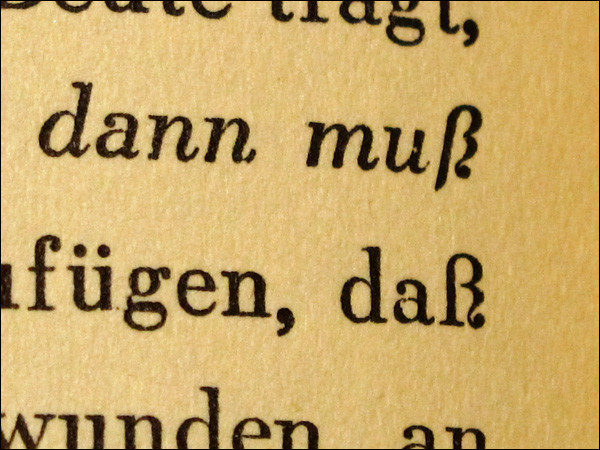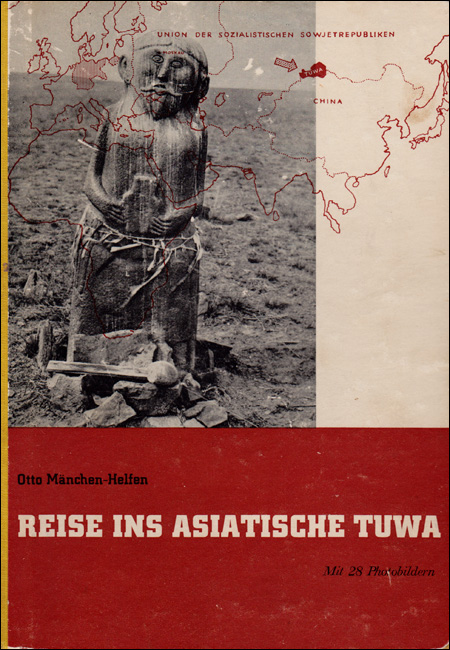
Liegt es daran, dass ich in Grammatik schon immer nicht so gut war oder ist das so geschrieben, als wäre die Typografin selbst die tastaturgesteuerte Anlage? :hammer:
Das ist doch mal ein gutes Argument für die Abschaffung des grammatischen Gleschlechts für Dinge! 8-)
nee, für bessere texte. hätte man ›dies war die erste tastaturgesteuerte anlage‹ geschrieben oder im selben satz nach einem komma bzw. gedankenstrich mit ›der ersten tastaturgesteuerten anlage‹ weitergemacht, wären missverständnisse dieser art ausgeschlossen. und grammatikalisches geschlecht ist viel zu praktisch, um es (selbst für nicht-lebendes) aufzugeben.
grammatikalisches geschlecht ist viel zu praktisch, um es (selbst für nicht-lebendes) aufzugeben.
Inwiefern? Was ist daran praktisch, dass es die Lampe heißt und der Ball?
Und – ich kann es mir einfach nicht verkneifen – ist es genauso praktisch wie die Unterscheidung zwischen Groß- und Kleinschreibung?
Hm. Im Afrikaans gibt es nur »die«. Reicht eigentlich auch. Warum haben wir denn drei Artikel, wer hat’s erfunden? :-?
Aber das Thema sollten wir vielleicht lieber in die Sprachpflegeabteilung zu Dr. Pachulke überweisen?
Hm. Im Afrikaans gibt es nur »die«. Reicht eigentlich auch. Warum haben wir denn drei Artikel, wer hat’s erfunden? :-?
Die Indogermanen.
Und die Römer sind schuld, dass wir das eine weiblich nennen, weil die Frau in deren Auflistungen zu diesem Genus an oberster Stelle stand.
Eigentlich war mal alles masukulin, dann erfand man das Neutrum für abstraktere Dinge, die meist im Akkusativ stehen und vorher eigentlich nicht als Nomininativ verwendet werden konnten, was dann aber doch ging und schließlich das Femininum für eine Ansammlung von vielen abstrakten neutralen Dingen.
Dies ist die Geschichte laut Herrn Scholten.
Am Ende wird eh alles männlich, wenn das ganze Gebilde zusammenbricht oder ein Wort aus einer anderen Sprache kommt, die keine Artikel/Genussystem mehr verwendet.
Du meinst so was wie »Event«, »Laptop« und »Blog«? Wobei sich da ja die Geister über die Artikel streiten …
Oder auch Punkt von punctum. Dieses Thema wird in diesem Video auch irgendwann angesprochen.
Inwiefern? Was ist daran praktisch, dass es die Lampe heißt und der Ball?
der vergleich von grammatikalischem geschlecht mit groß- und kleinschreibung ist nicht mal so schlecht. notwendig ist beides nicht, aber es kann manches erleichtern. mit genus kann man bequemer auf dinge bezug nehmen. auf deutsch kann ich sagen: ›der ball hat die lampe beschädigt. er/sie (bzw. der/die) war ein geburtstagsgeschenk.‹ – und sofort weiß man, was das geschenk war, der ball oder die lampe. natürlich ist das kein unfehlbares system (so wie auch groß- und kleinschreibung nicht alle mehrdeutigkeiten beseitigt), aber in kombination mit kasus kommt man damit schon recht weit. andere sprachen können die entsprechenden inhalte natürlich ebenso ausdrücken, aber es ist ein nettes extra, das sprachen ohne genus eben nicht bereithalten. die haben dafür wieder andere sachen.
Ein für mich tolles ß aus einem von Jan Tschichold gestalteten Buch (1931):
Die Schriftart wird im Buch jedoch leider nicht genannt.
Klasse, danke! Dann kam die Schrift ja nur wenige Jahre vor dem Buch auf den Markt.
Ja – bei dem Buch handelt es sich um „Reise ins asiatische Tuwa“ von Otto Mänchen-Helfen, erschienen 1931 im Verlag Der Bücherkreis GmbH, Berlin SW 61.
Die für den Autor und den Titel verwendete Schrift sieht mir nach der City (halb-)fett von Berthold aus.
Besten Dank für die Abbildung. Das ist eines der wenigen Bücher, bei dem sich Tschichold für einen kaschierten Halbleinenband entschieden hat.
Danke für dieses Detail! – Sehr schön ist natürlich auch das Logo des Bücherkreises, aber das dürfte hier bekannt sein (wenn nicht, mache ich gerne einen Scan).
Interessanterweise gab es (mindestens) drei Versionen des Signets, darunter ein Entwurf von Jan Tschichold. Wenn Interesse besteht, schaue ich in den kommenden Tagen, ob ich alle drei gescannt bekomme.